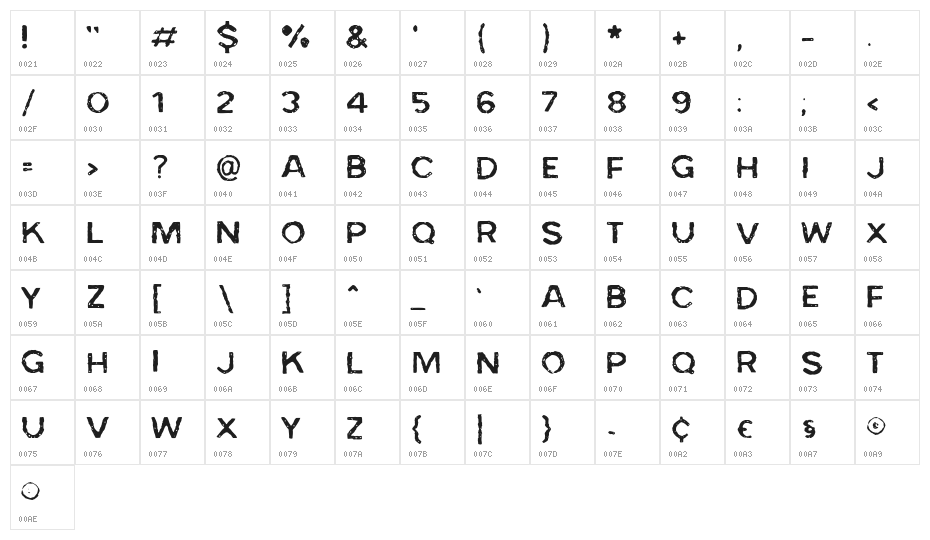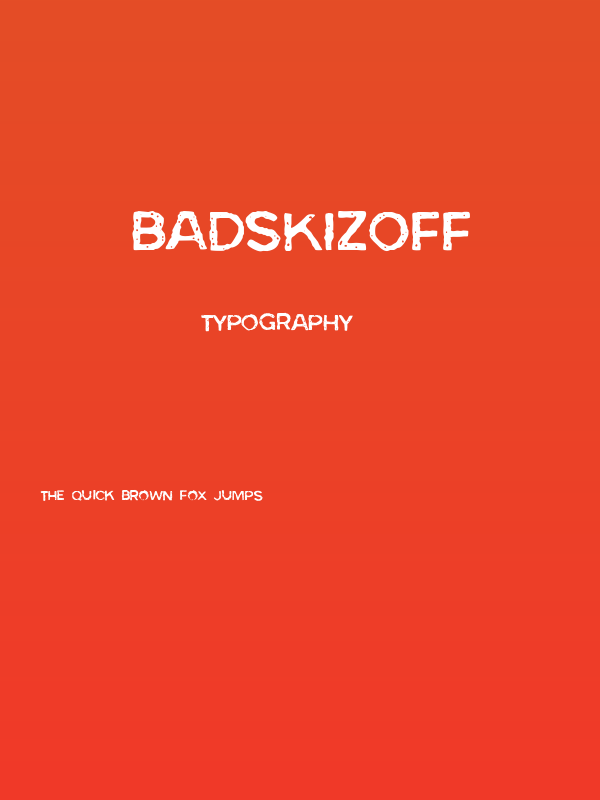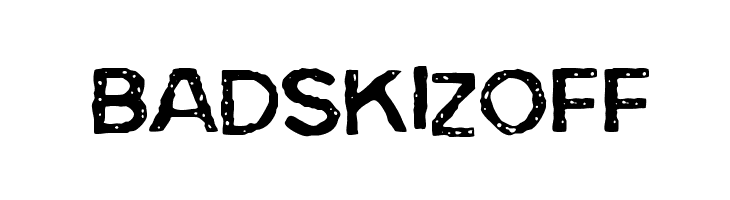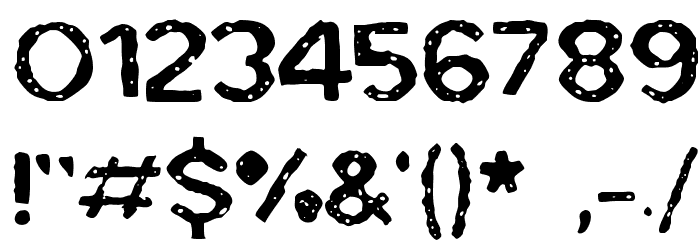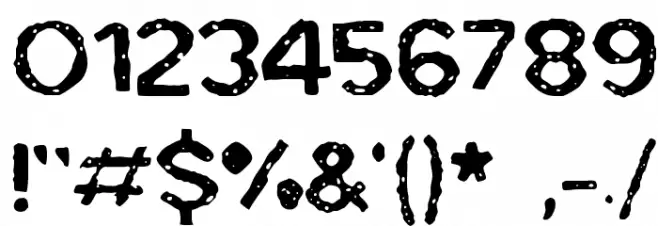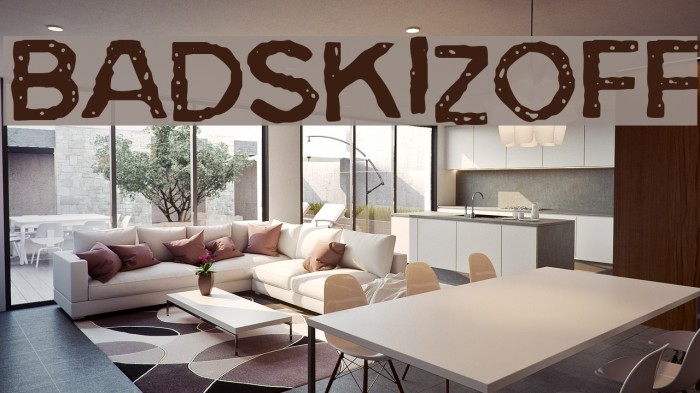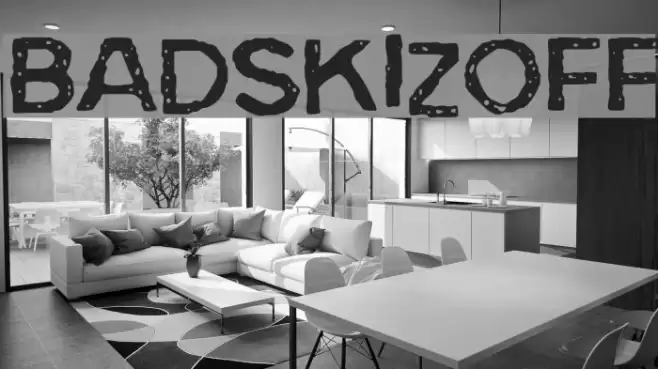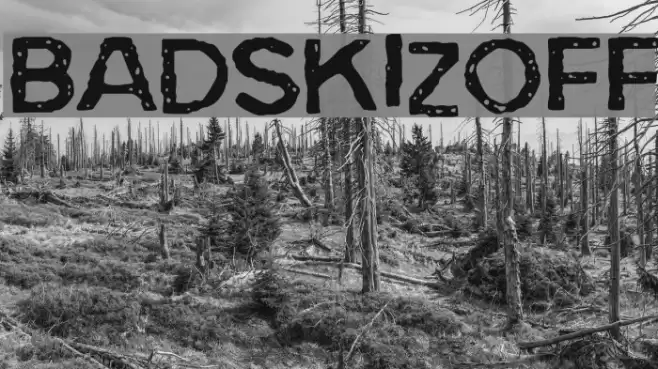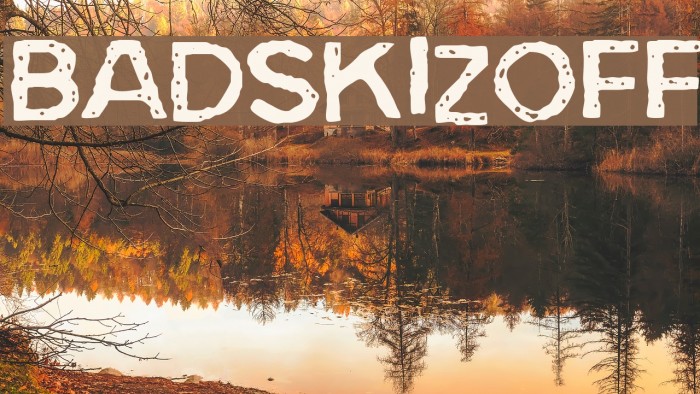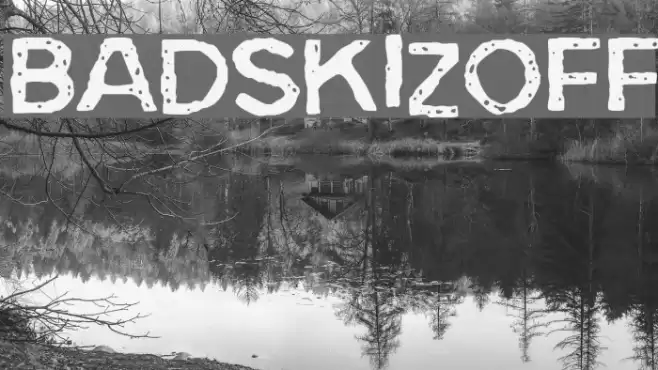
BadSkizoff Font
✎ Distorted Eroded
Fonts by Bumbayo Font Fabrik
BADSKIZOFF 大文字
BADSKIZOFF 小文字
BADSKIZOFF その他の文字
| カテゴリ | Distorted Eroded |
| おすすめプロジェクト | Ideal for posters, children's book covers, playful branding, and creative social media graphics. |
| 作者 | Fonts by Bumbayo Font Fabrik |